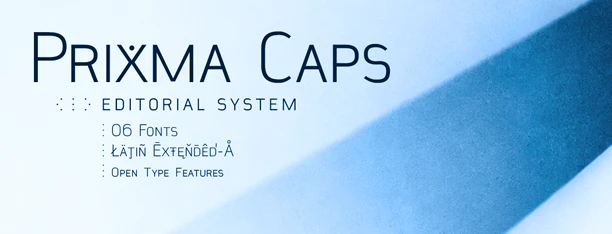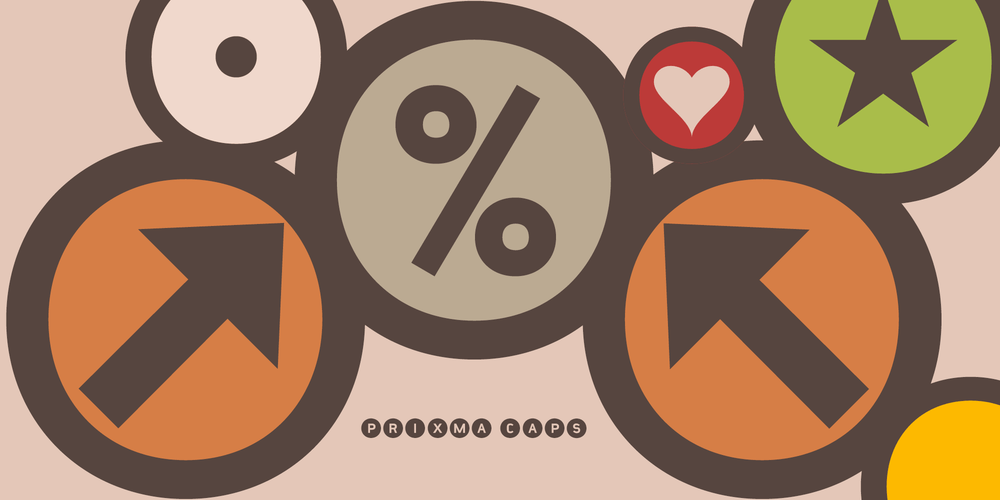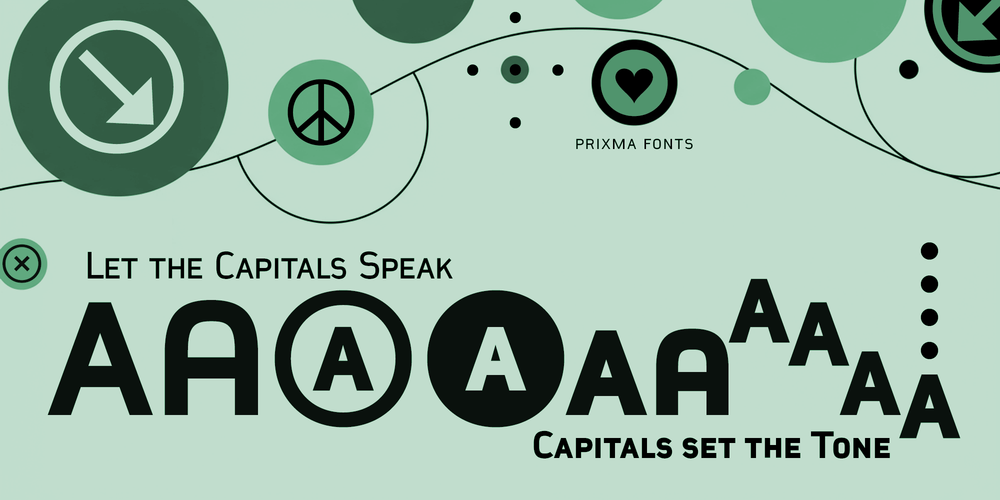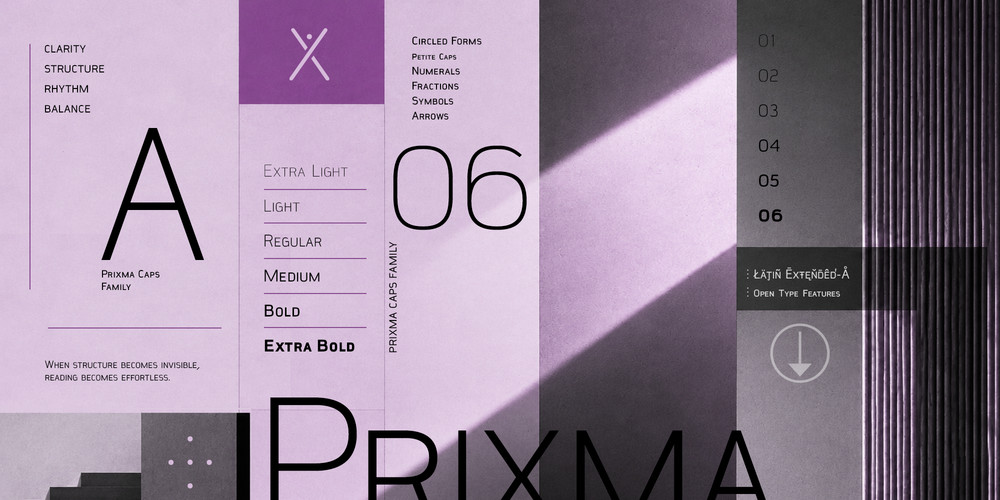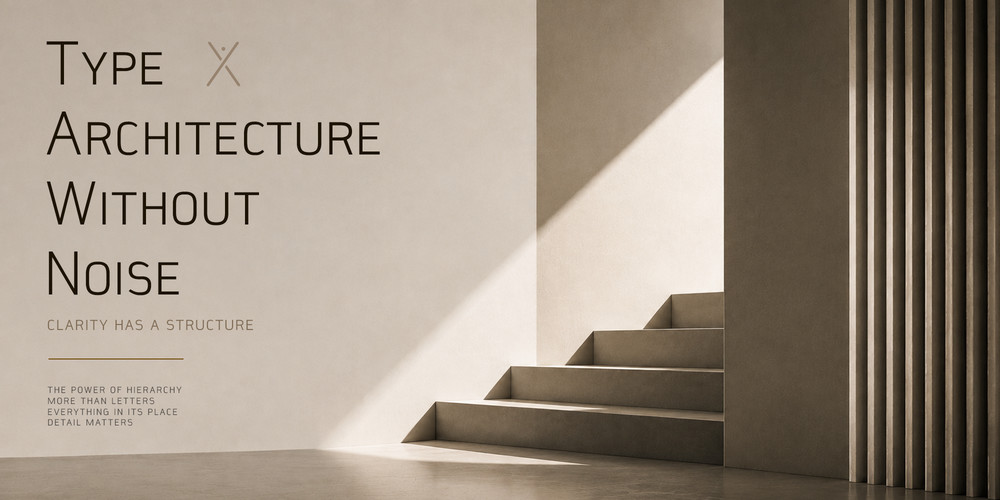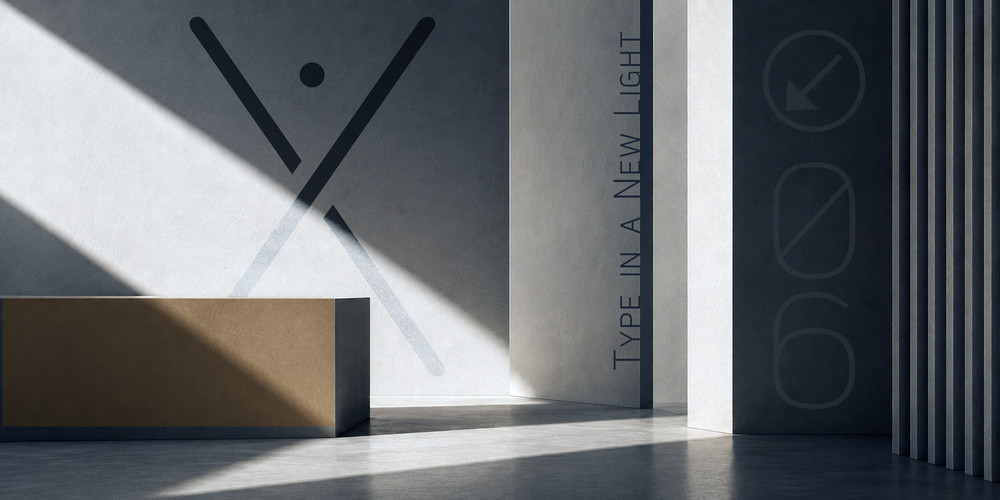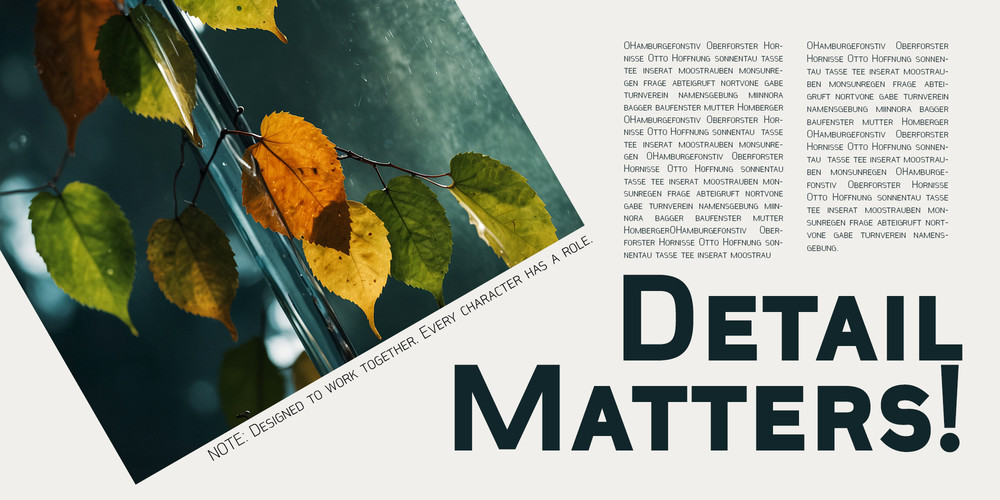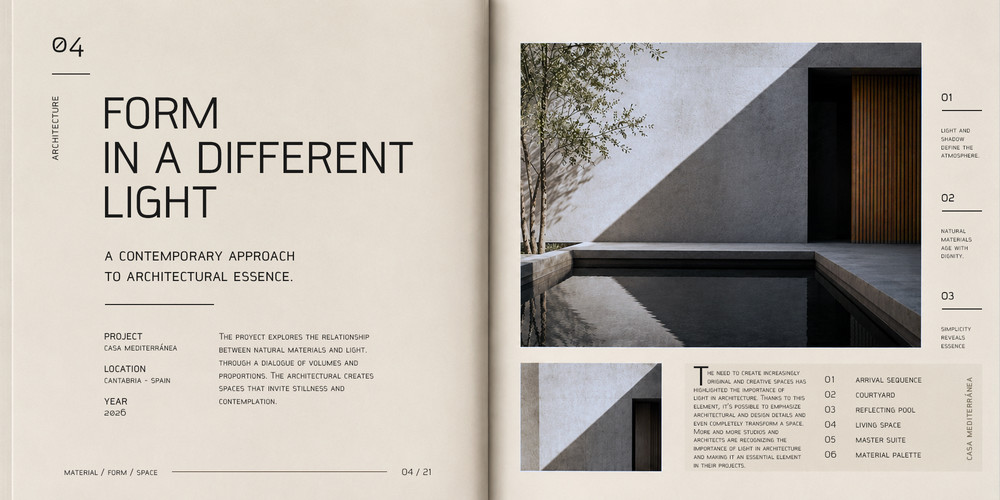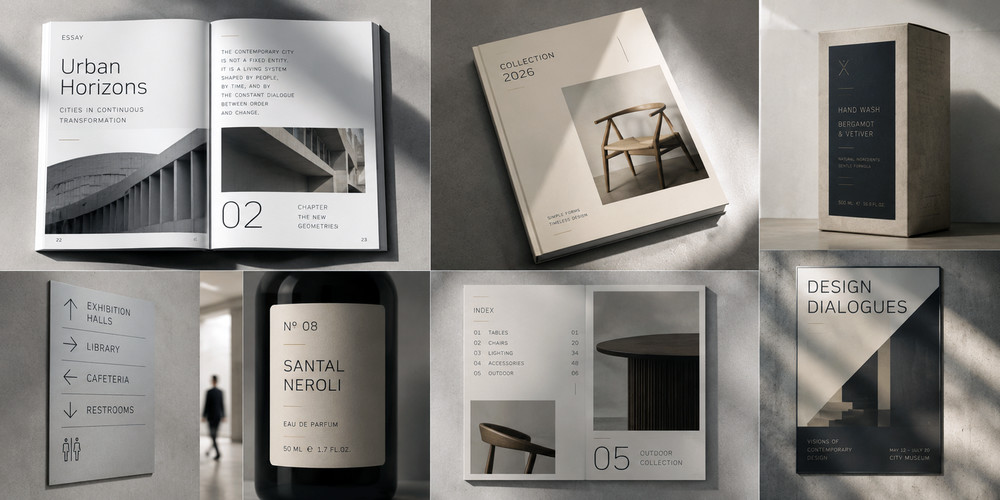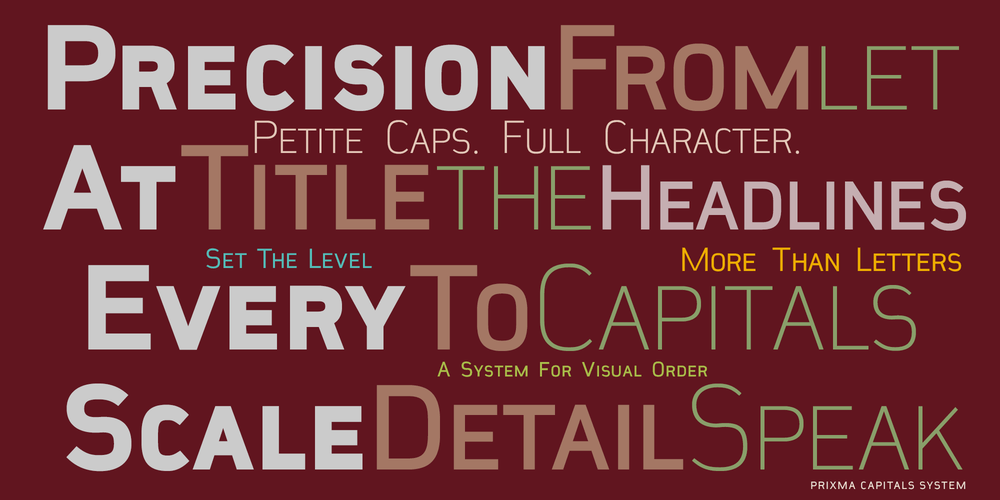
Prixma Caps es la extensión de Prixma Sans concebida para trabajar con mayúsculas, jerarquías y composición tipográfica. Mantiene el carácter geométrico, preciso y ligero de Prixma Sans, pero lleva su lenguaje hacia un territorio más gráfico y expresivo, especialmente adecuado para titulares, identidad visual, diseño editorial y branding.
Prixma nació como una familia sans serif de ritmo contemporáneo, diseñada para funcionar tanto en textos pequeños como en composiciones de mayor escala. Prixma Caps parte de ese mismo ADN y lo desarrolla desde otra perspectiva: más estructura, más contraste de escala y más posibilidades de composición.
No se trata simplemente de utilizar las mayúsculas de Prixma Sans a mayor tamaño. Prixma Caps está construida como un sistema propio, capaz de establecer diferentes niveles de información dentro de una misma composición.
Un sistema para organizar la información
La arquitectura de Prixma Caps permite combinar diferentes escalas y pesos para construir jerarquías claras sin perder continuidad visual.
Los seis pesos de la familia —Extra Light, Light, Regular, Medium, Bold y Extra Bold— permiten recorrer un amplio espectro, desde composiciones extremadamente ligeras hasta titulares de gran presencia.
Esta amplitud convierte Prixma Caps en una herramienta particularmente versátil para revistas, libros, catálogos, carteles, packaging, identidad corporativa, interfaces y sistemas gráficos.
Su diseño busca que la jerarquía no dependa únicamente del tamaño. Peso, escala, ritmo y proporción pueden trabajar conjuntamente para construir diferentes niveles de lectura.
Petite Caps y múltiples escalas
Uno de los recursos más particulares de Prixma Caps son sus Petite Caps.
Las formas minúsculas se han desarrollado también en posiciones tipográficas específicas para generar pequeñas capitales, permitiendo introducir un nivel intermedio entre el texto convencional y las mayúsculas. El resultado es especialmente útil para subtítulos, etiquetas, referencias, información secundaria, índices y pequeños bloques editoriales.
La familia incorpora además diferentes sistemas de numeración y escalado, incluyendo Old Style Figures, superiores, inferiores, numeradores y denominadores. Las posiciones numr y dnom permiten construir fracciones dinámicas mediante la función frac, mientras que sups, subs y sinf proporcionan las correspondientes formas superiores e inferiores.
Más que una colección de letras
Prixma Caps incorpora un amplio conjunto de caracteres y recursos OpenType que permiten utilizar la tipografía también como elemento gráfico.
Entre ellos encontramos formas circulares para letras y números, símbolos, flechas, signos matemáticos, ordinales, fracciones, alternativas contextuales, ligaduras y caracteres especialmente diseñados para determinadas combinaciones.
Las ligaduras discrecionales amplían todavía más este repertorio, transformando determinadas combinaciones de caracteres en signos, símbolos y pequeñas construcciones gráficas.
De este modo, Prixma Caps puede comportarse como una tipografía convencional cuando se necesita claridad, o convertirse en una herramienta gráfica cuando la composición pide algo más.
Latin Extended-A
Prixma Caps incluye soporte para Latin Extended-A, junto con un conjunto de caracteres acentuados diseñado de acuerdo con el lenguaje formal de la familia. El espécimen incluye, entre otros, caracteres utilizados en diferentes lenguas europeas y sus correspondientes formas acentuadas.
Esto permite utilizar la familia en proyectos editoriales y de identidad visual que requieren una cobertura lingüística más amplia que el alfabeto latino básico.
Diseñada para la página
Prixma Caps encuentra uno de sus espacios naturales en el diseño editorial.
Titulares, capítulos, índices, pies de fotografía, numeración, etiquetas, referencias y pequeños bloques de información pueden convivir dentro de un mismo sistema tipográfico. La posibilidad de combinar mayúsculas, Petite Caps, numerales y diferentes pesos permite construir páginas con una jerarquía precisa sin necesidad de recurrir constantemente a familias tipográficas diferentes.
- Symbols & Arrows
- Mathematical Symbols
- Special characters & typographic symbols
Una familia que continúa creciendo
Prixma Sans nace como una familia abierta. Prixma Caps es la primera variante desarrollada a partir de Prixma Sans.
La familia Prixma continuará explorando otros territorios formales. La siguiente variación prevista es Prixma Slab Serif, que trasladará el lenguaje de Prixma Sans hacia una interpretación slab serif.